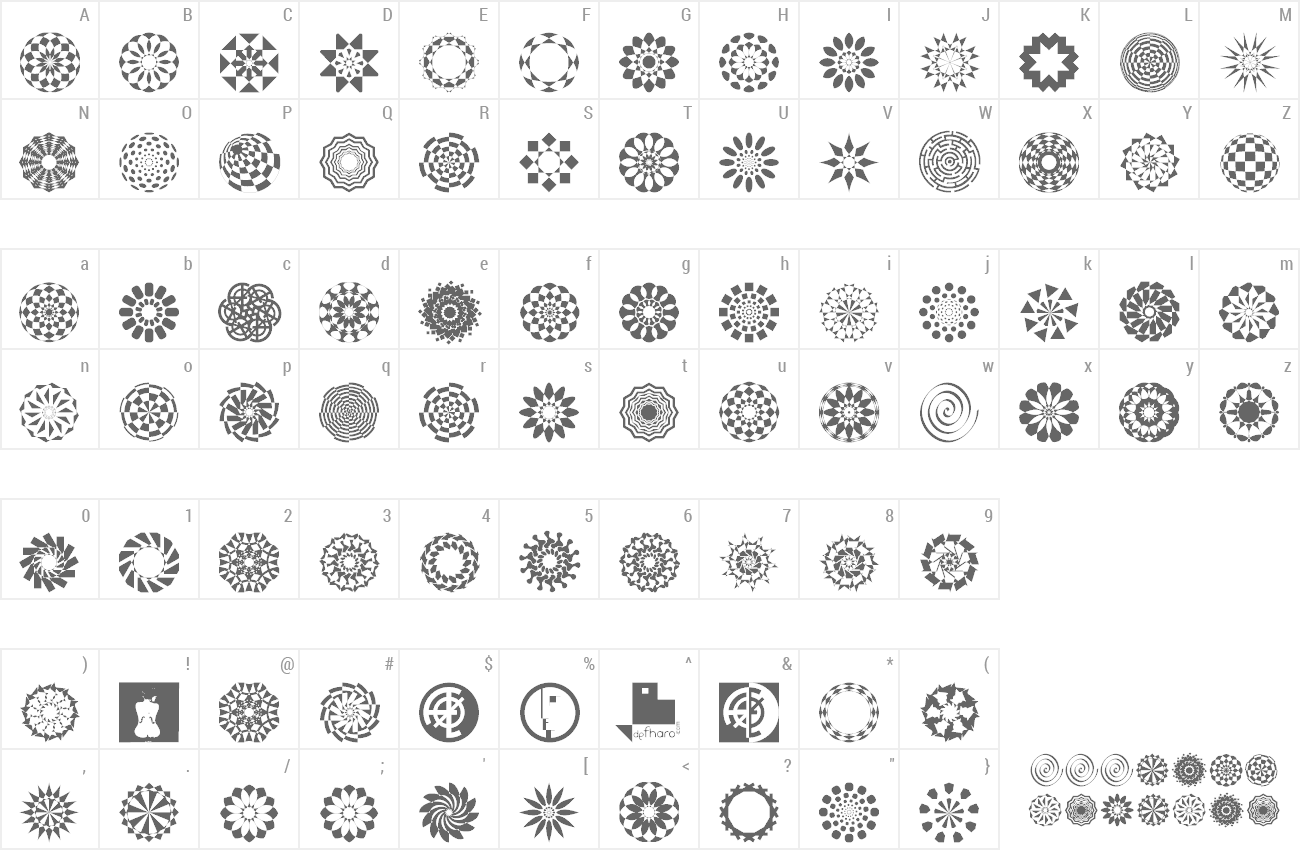
| Font name: | Wach Op-Art |
| Categories | Dingbats, Shapes |
| Author: | deFharo |
| Note by deFharo | |
95 Clip art in a font! Esta colección de Clip art ha nacido de formas geométricas básicas y complejas moviéndose y girando sobre el círculo, inspirada también en los diseños de la colección de relojes de diseño y más concrétamente a la serie Op-art creada por mí al final de los 80. • Only for personal use. Sólo para uso personal. • Licencia comercial disponible / Available commercial license.>> http://defharo.com/fonts/95-clips-online-gratis/ |